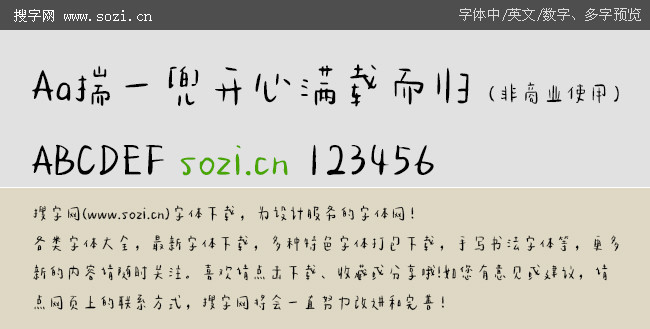
Aa揣一兜開心滿載而歸
搜字網(wǎng)給大家提供一款A(yù)a揣一兜開心滿載而歸(非商業(yè)使用)字體下載,該字體是一款不錯的卡通藝術(shù)字體,這款字體為兒童手寫風(fēng)格,字形夸張,充滿童趣。適合書裝設(shè)計、包裝設(shè)計、海報設(shè)計等應(yīng)用(此字體為個人非商用版,商用可以聯(lián)系QQ:1006760504)。